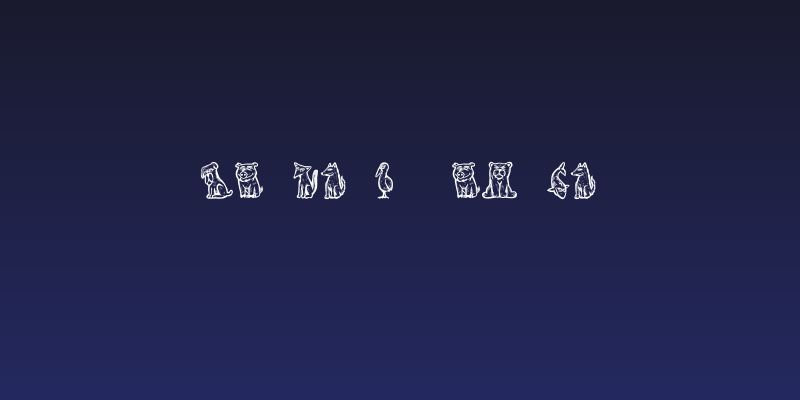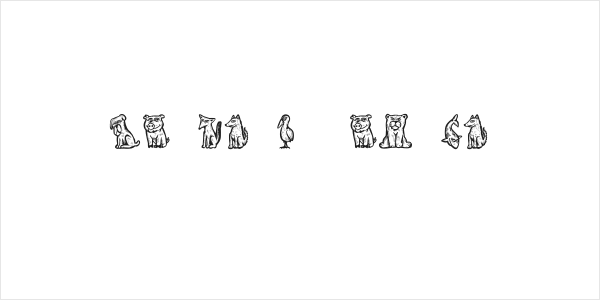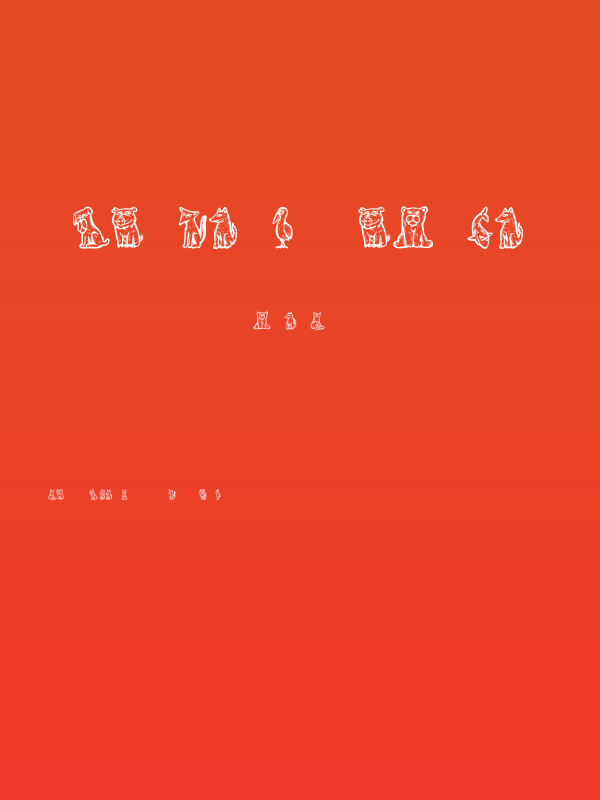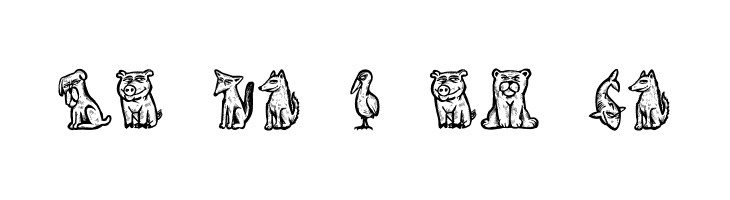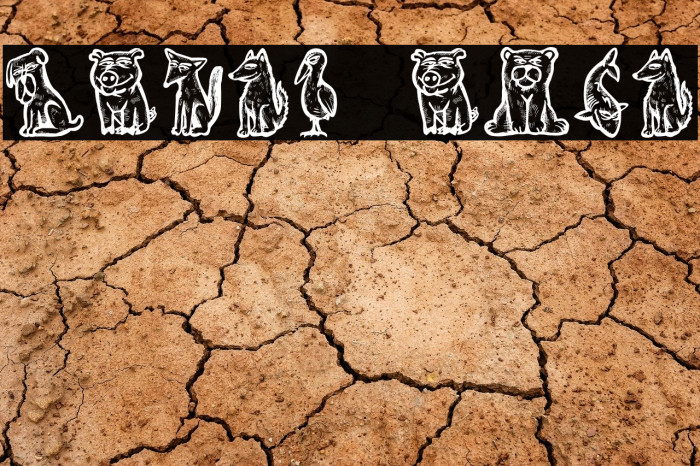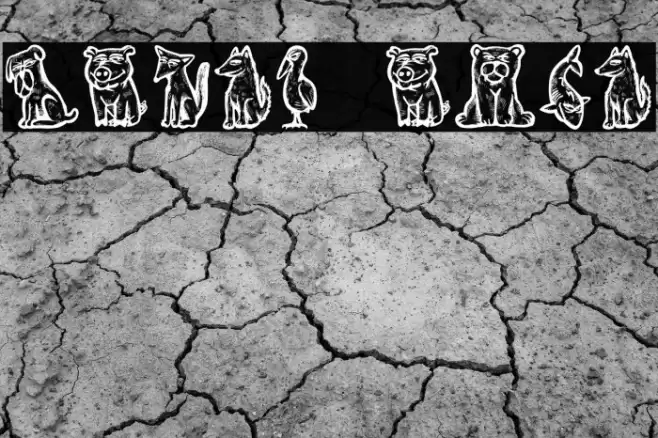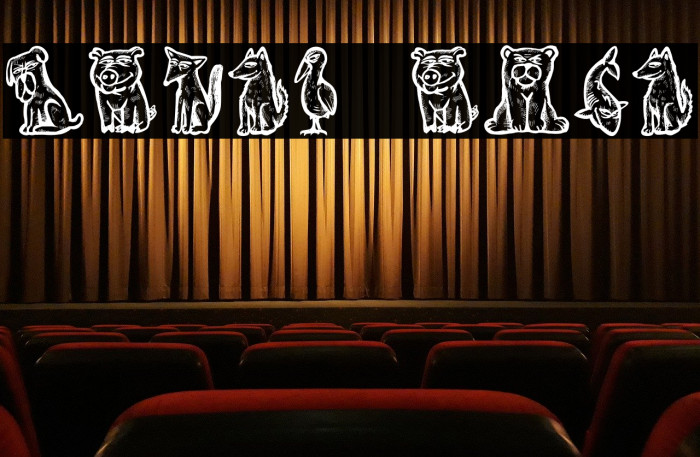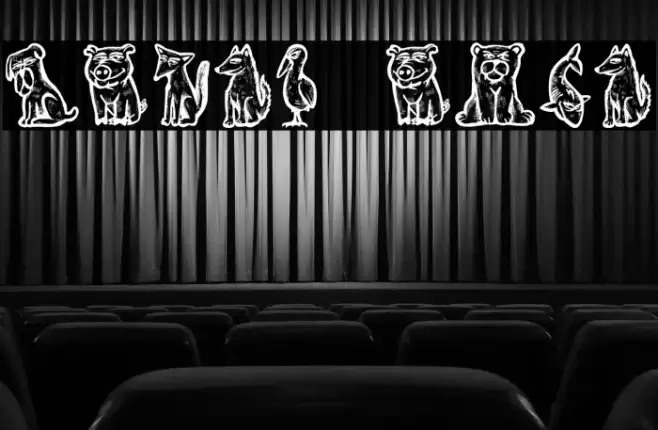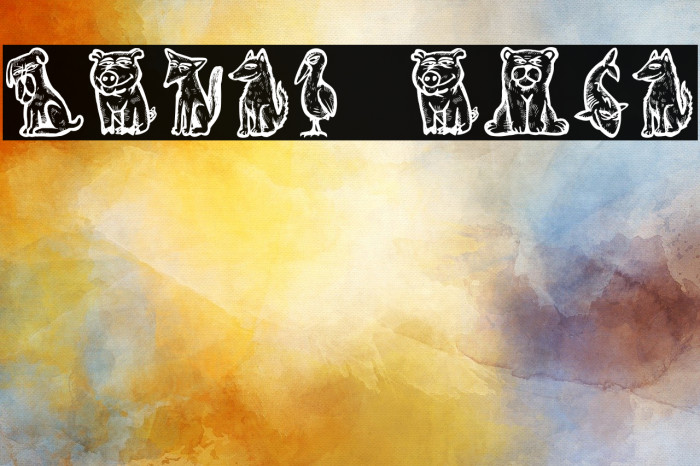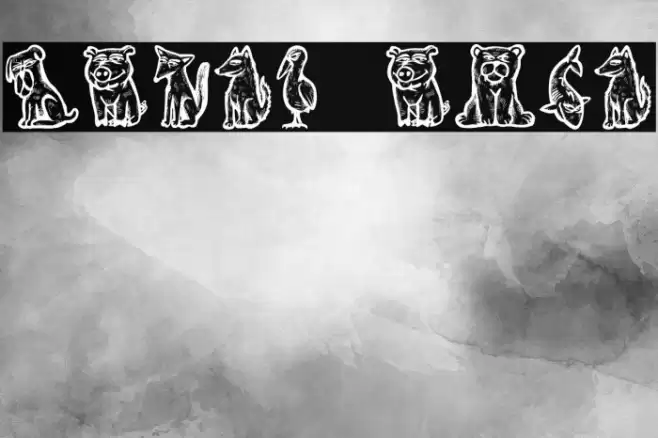
Tierfarm Regular Font
| Stile generale | Playful, Artistic, Whimsical |
| Caso d'uso | Logos, Decorative headings, Children's materials |
| Progetti proposti | Ideal for children's books, playful branding, themed event materials, and creative design projects. |